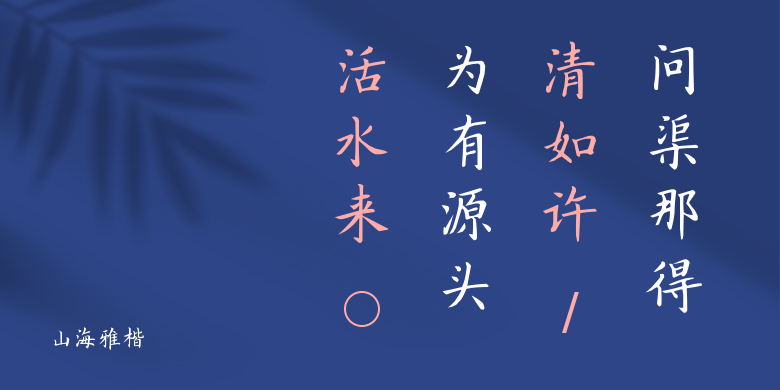
山海雅楷
山海雅楷,这款字体结构工整、笔画清晰,兼顾美观与易读性,适用于标题、正文、海报、包装、LOGO 等多种场景。字形优雅稳定,风格百搭耐看,适配日常排版与创意设计,让文字呈现更舒适、更具质感。山海雅楷一笔一画,皆是细节,以均衡的比例、流畅的线条打造舒适视觉体验,字形端正大气,风格简约现代。无论是商业设计、品牌宣传还是日常排版,都能轻松驾驭,让文字更有格调与力量。山海雅楷字体下载。